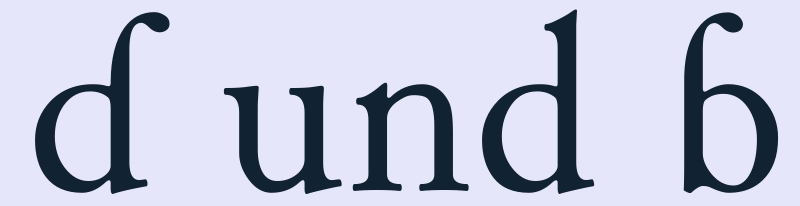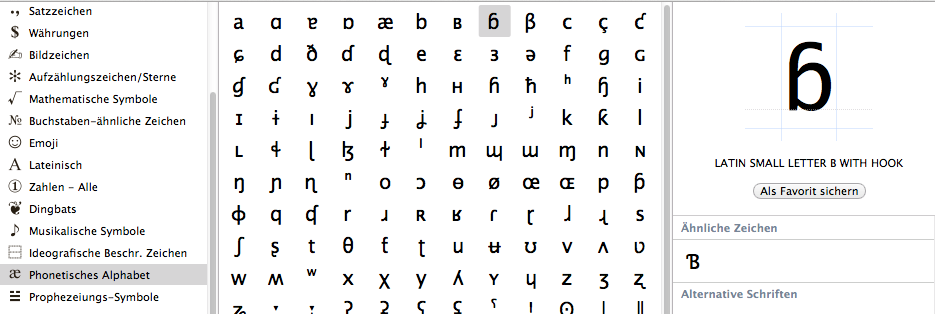
b mit Haken in Garamond
Ein bekannter von mir setzt wissenschaftliche Arbeiten und sitzt nun an einem Buch wo IPA-Zeichen benötigt werden. Der Verlag, der das nachher herausgibt besteht auf Garamond – was auch immer das heißen mag, wenn man bedenkt wie weit das Feld der Garamonden aufgestellt ist.
Er hat wohl diverse Garamond-Versionen zur Verfügung (z. B. Garamond Premiere) und einige durchgeguckt, ihm fehlen aber zwei Zeichen, die scheinbar nirgendwo bei sind.
Es handelt sich um ɗ und ɓ
Weiß irgendwer eine Garamond in der diese Zeichen enthalten sind? (EB Garamond hat sie wohl auch nicht)
Entweder man exekutiert kurz und dreckig irgendeinen Hack und schweigt, oder man schaut sich vorher an, ob die eingesetzte Schrift das benötigte Repertoire abdeckt – oder ob man eine Schrift wählt die für die Aufgabe geeignet ist.
Dieses kindische Geningel »mir fehlt ein Zeichen hu hu« kann ich nicht mehr hören. Das nervt.
Die beiden hier fraglichen Zeichen gehören übrigens nicht zum IPA-Satz, das nur am Rande.
Sondern?
Ich habe das jetzt nicht besonders recherchiert, sondern ich dachte mir, fragste mal Leute, die sich auskennen ... Könnte ja der Sinn eines Forums sein 8-)
Dieses »Ich bin der coole Designer huhuhu und alle anderen sind kindisch« statt zu helfen oder zu schweigen, kann ich auch manchmal nicht mehr hören
Edit: Die EB Garamond hat sie wohl doch ?!
Vielleicht hat er die stumpf nicht gefunden, weil er sie im IPA-Satz gesucht hat :-?
Hab mir gerade mal aus Neugier ein bisschen IPA in verschiedenen  Schriften angesehen – das variiert gestaltungstechnisch doch ganz schön. Zum Beispiel hat das besagte b mit Knick manchmal einen ebensolchen, manchmal auch eher ein Fähnchen oder einen Tropfen – und meist sieht es aus wie ein umgedrehtes g. Verwirrend. Da bin ich doch froh, dass Chinesisch (in der Variante putonghua) phonetisch so überschaubar ist ...